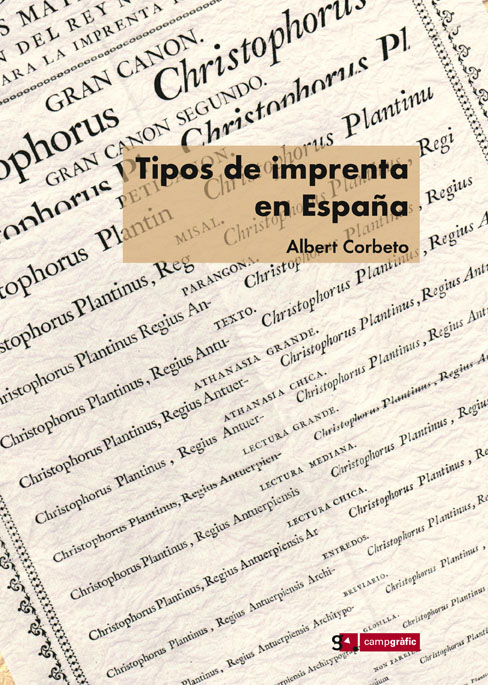
Tipos de imprenta en España es el libro que acompaña a Daniel B. Updike impresor e historiador de la tipografía, que comentamos hace poco, que han sido escritos por el investigador e historiador de la tipografía Albert Corbeto y que han sido publicados conjuntamente en un verdadero «tour de force» por la Editorial Campgràfic.
En este libro el autor nos detalla la producción y comercialización de tipos de imprenta en España desde el periodo incunable hasta las tipografías decimonónicas que aparecen con el establecimiento en España de las fundiciones industriales a finales del siglo XIX.
Siguiendo a la reflexión de Corbeto si bien las tipografías del periodo incunable en España están bien estudiadas y analizadas en numerosos trabajos de amplio calado, también es verdad que las posteriores a esta época estaban prácticamente huérfanas, esperando a poder ser catalogadas y ayudar a una articulación de la historia de la imprenta y del libro en este país.
Dicho esta no nos queda otra que dar la bienvenida efusivamente a esta nueva obra del investigador catalán, que complemente a otra suya titulada Especímenes tipográficos españoles. Catalogación y estudio de las muestras de letras impresas hasta el año 1833 y publicado por la Editorial Calambur, y felicitarnos por tener en nuestras manos un material de estudio de primer orden que nos posibilita poder avanzar en los estudios antes citados.
Coincidimos con el autor en la tradicional dependencia de materiales de imprenta sufrida por España a lo largo de su historia, como el principal motivo para la falta de bibliografía al respecto. Incluso en el periodo en el que la imprenta española gozó de alta estima en Europa que fue la segunda mitad del siglo XVIII la referencia a los grabadores de punzones ha sido escasa. Esta falta de «noticias» que hizo exclamar a Stanley Morison su «escandaloso desconocimiento» sobre los tipos de imprenta españoles con esta obra podemos decir que ha quedado felizmente superado.
Con unos recursos y unas fuentes bibliográficas apabullantes, fruto de una minuciosa búsqueda en archivos y bibliotecas, Albert Corbeto nos invita a disfrutar en las páginas de su obra de un conocimiento amplio, detallado y riguroso de los tipos de imprenta utilizados en España y no dudamos de que su obra abrira la puerta a futuras investigaciones que enriquezcan los conocimientos sobre el tema.
Si los dos capítulos de la obra de Updike Printing Types dedicados a España era el acercamiento más sistemático a nuestros materiales tipográficos, Tipos de imprenta en España nos situa sin ningún género de dudas, al nivel del resto de paises europeos en cuanto a material bibliográfico de consulta sobre la creación y comercialización de estos.